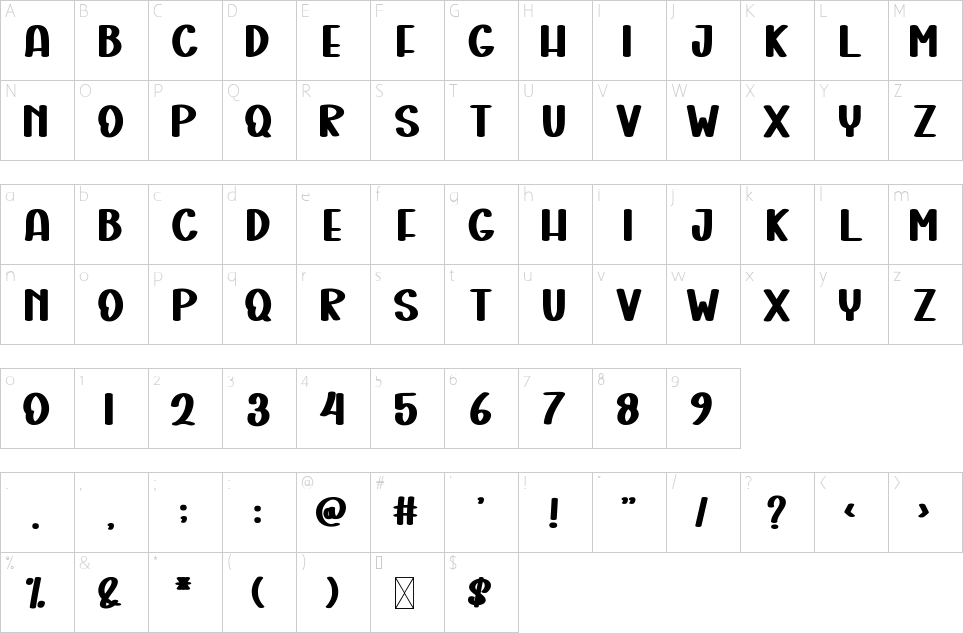
Modern Designer é uma elegante e moderna fonte gráfica que é perfeita para designers digitais que procuram uma opção de fonte versátil. Ela foi projetada por InermediaSTUDIO e é uma opção gratuita, ideal para quem deseja adicionar um toque de sofisticação a seus projetos. A fonte Modern Designer está disponível para sistemas Windows e Mac, tornando-a uma opção conveniente para designers que trabalham em diversos ambientes de trabalho. Com sua arquitetura minimalista e estilo moderno, a Modern Designer é uma escolha conveniente para criações que exijam uma aparência de design limpa e contemporânea. Com a Modern Designer, você não só adiciona uma paleta de cores a seu design, mas também oferece um toque sofisticado que pode dar um jeito ao seu trabalho gráfico.